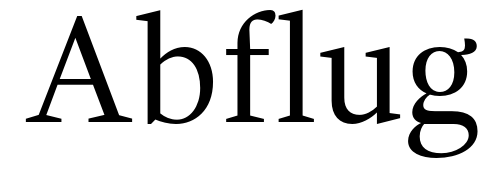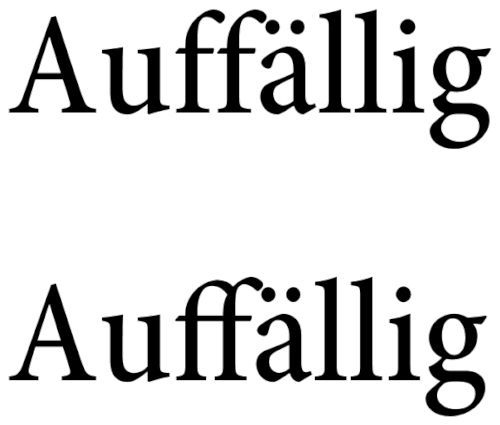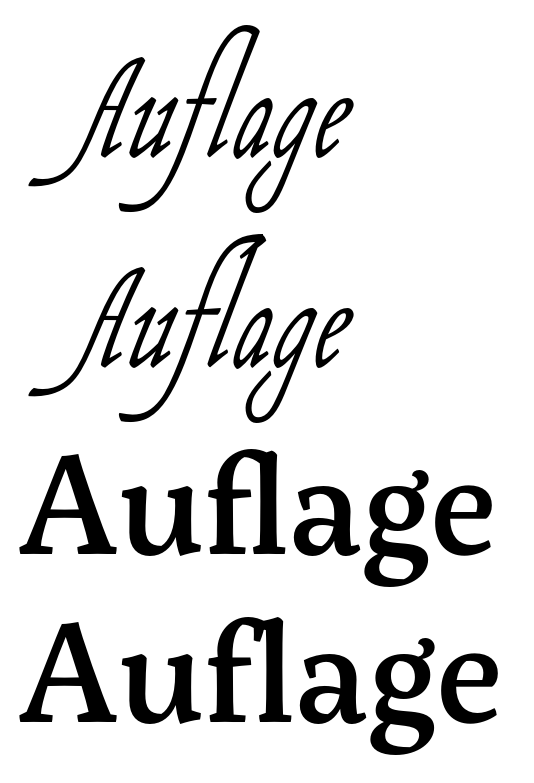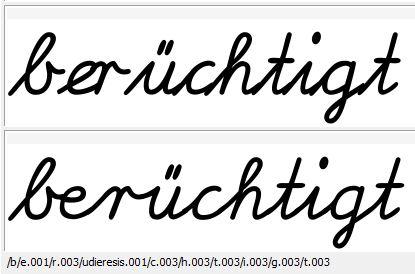
Word 2013 - Einzelne bzw. bestimmte Ligaturen aktivieren
in folgender Sache bitte ich um Hilfe: Wie bekannt sein dürfte, bietet Word 2013 die Möglichkeit, das Programm automatisch Ligaturen setzen zu lassen, und dies sogar regelgemäß, soweit ich es beurteilen kann. So löblich diese Funktion ist, so eingeschränkt sind doch die Möglichkeiten der Auswahl, denn Word bietet nur vier Modi:
Standard
Standard und kontextbezogen
Historisch und frei
Alle
Meinerseits würde ich die Modi gerne verändern. Genauer gesagt, ich möchte letztgenannten Modus anwenden, doch eine Ausnahme einbauen, nämlich diejenigen für meine Zwecke allzu extravaganten Ligaturen deaktivieren, die einen Konsonanten und 't' mit einem Bogen verbinden (z.B. 'st'). Ist das möglich?
(Auch wenn ich darauf hoffte, eine Liste manuell bearbeiten zu können, wie bspw. die Liste der Autokorrekturen analog. So ist nämlich eine manuelle Nachbearbeitung jeder Ligatur nötig.)
Du kannst dir die Arbeit möglicherweise erleichtern, indem du eine Zeichen-Formatvorlage erstellst und dort die Ligaturunterstützung änderst/einschränkst oder gar entfernst. Nenne sie beispielsweise »KeineLigatur« oder »Ligaturtyp2«. Weise diese Vorlage allen Vorkommen zu, bei denen die Ligatur gesperrt/eingeschränkt sein soll.
Das geht ggf. auch über Suchen/Ersetzen. Das Schöne: Man kann auch einen Begriff ohne Vorlage mit einem mit Vorlage ersetzen. So könntest du alle Vorkommen von »Konfiguration« durch »Konfiguration« (mit Zeichenvorlage Soundso) ersetzen lassen.
Vielleicht lässt sich damit so eine Art Halbautomatik realisieren.
Noch ein Tipp: Weise der Zeichenvorlage probeweise eine Farbe zu, damit du siehst, was wo wie ersetzt wurde. Die Farbe kannst du später problemlos entfernen.
Ich muss noch einmal diesen Strang ausbuddeln und um Hilfe bitten: Hat jemand Microsoft Word, vorzugsweise 2013, und kann für mich kurz nachsehen bzw. bestätigen, ob die Ligaturensetzung (Standard-Modus) dort tatsächlich regelkonform stattfindet, das heißt, nicht über Wortfugen hinweg?
Heute früh fiel ich aus allen Wolken, als mir erstmal auffiel, dass ein Dokument, welches ich vor einigen Monaten erstellt hatte, durchgängig nur Ligaturen enthält, also auch regelwidrige wie bspw. eine fl-Ligatur in Auflage. Ich meine mich zu erinnern, damals das Gegenteil beobachtet zu haben, und möchte ausschließen können, ob falsche Einstellungen oder gar ein Update in der Zwischenzeit mein liebliches Schriftbild über den Haufen geworfen haben.
Außer Spezialprogrammen/-plugins/fonts, die etwa für Fraktursatz gemacht sind, kenne ich überhaupt keine Satz- und Layout-Programme, die von sich aus Ligaturen nach Inhalt anwenden oder auflösen. Die Ligaturen sind entweder generell an oder aus. Alles andere muss manuell gemacht werden.
…und dies sogar regelgemäß, soweit ich es beurteilen kann…
Was nützen dann überhaupt die in Word möglichen Abstufungen wie "kontextbezogen", wenn eben kein Kontext berücksichtigt wird?
Kontext bezieht sich hier auf die Gestaltung der Schrift, nicht den Textinhalt. Kontextbedingte Ersetzungen finden statt, um z.B. Schreibschriften besser zu verbinden, wenn es der Kontext (also die umgebenden Zeichen) nötig machen.
Ich liefer hierzu mal ein Beispiel:
Oben die eingetippen Buchstaben, jeweils in der initialform, mit den Anstrich an der Schreiblinie beginnend.  unten die kontextsensitive Ersetzung, man beache die Buchstabenform mach b und r, bei denen die Verbindung noch weit höher stattfindet, als bei den anderen Buchstaben.
(Lateinische Ausgangsschrift, von mir für Worksheetcrafter)
Danke vielmals Euch beiden für die Antworten. Tja, wenn das so ist, scheint mir die einfachste (nicht am wenigsten arbeitsintensive, aber schlichst einfachste) Methode jedenfalls für Word 2013 zu sein, alle Ligaturen zu aktivieren und dann mit Bindehemmer diejenigen aufzubrechen, die Wortfugen ignorieren.
Allerdings würde ich mir gern eines der erwähnten Plugins ansehen, falls welche für Word 2013 angeboten werden.
Warum? Kein Leser, der nicht bewusst nach vermeintlichen Ligaturregelverstößen sucht, wird über solche Ligaturen stolpern. Ihre Funktion hat mit Wortfugen ohnehin nichts zu tun.